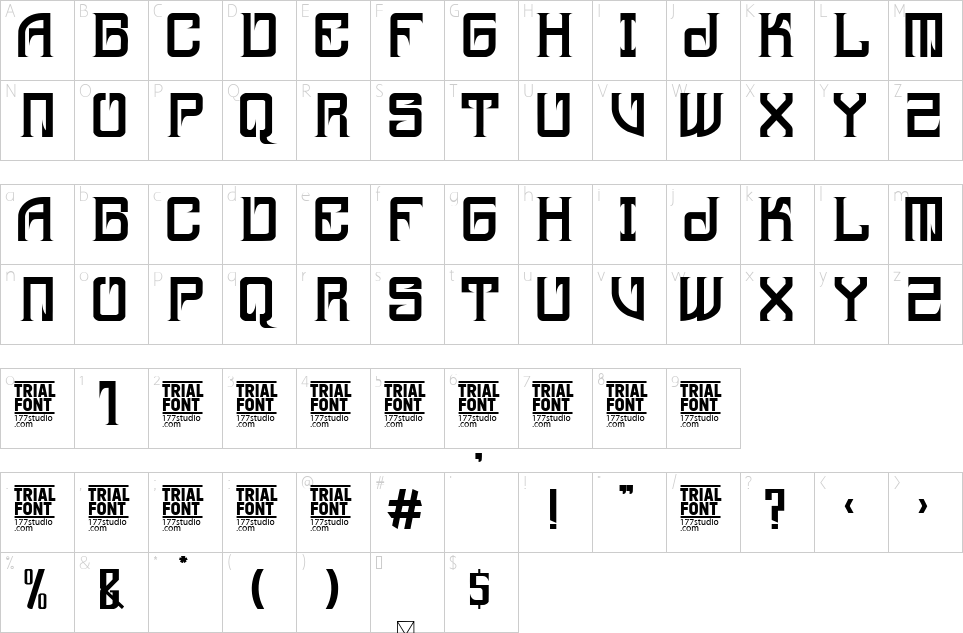
A Power Unique é uma fonte única e versátil, ideal para designers que buscam uma alternativa a fontes convencionais. Desenvolvida pelo site 177studio.com, essa fonte oferece uma aparência inovadora e personalizada, tornando-a perfeita para projetos que exigem destaque e originalidade. O design cuidadoso da Power Unique foi projetado para complementar qualquer tipo de layout gráfico, seja em design de sites, arte digital ou criação de impressões. Sua disponibilidade para uso em dispositivos Windows e Mac torna-a uma opção versátil para designers de todo o mundo. Com seu design exclusivo e fácil de usar, Power Unique é uma fonte gratuita que vale a pena experimentar. Há algo de tão bom quanto poder dar um toque único à sua próxima criação com essa fonte única.